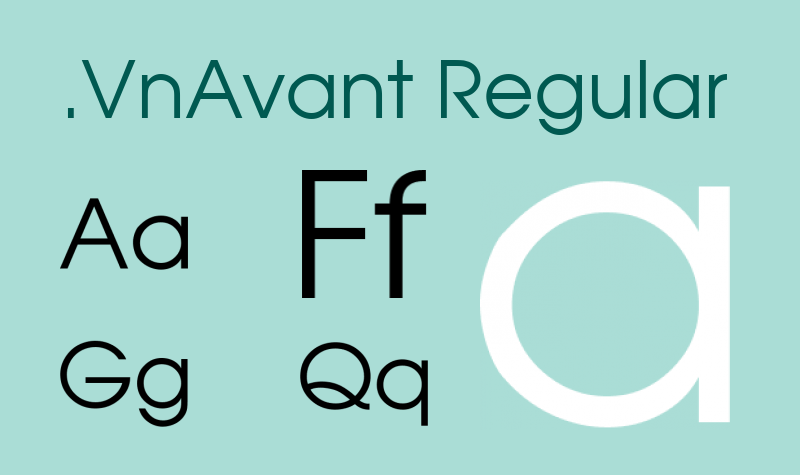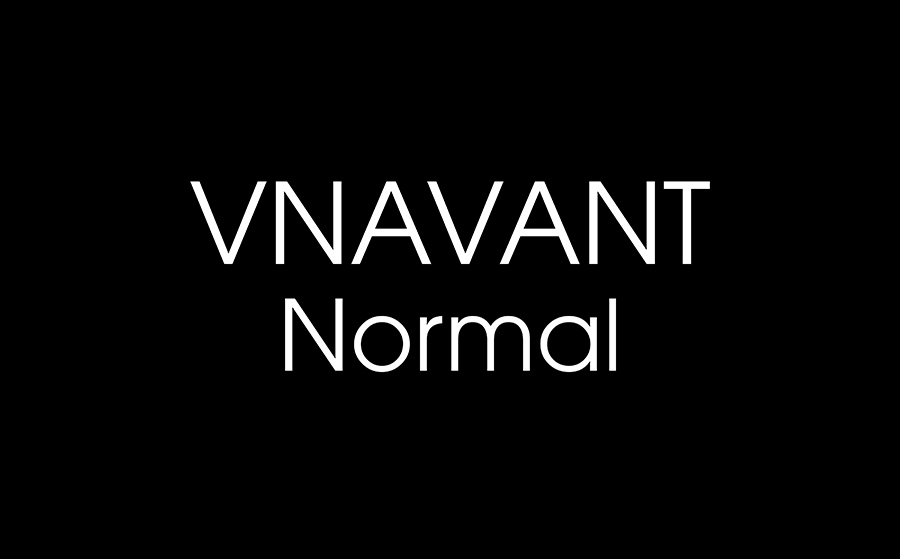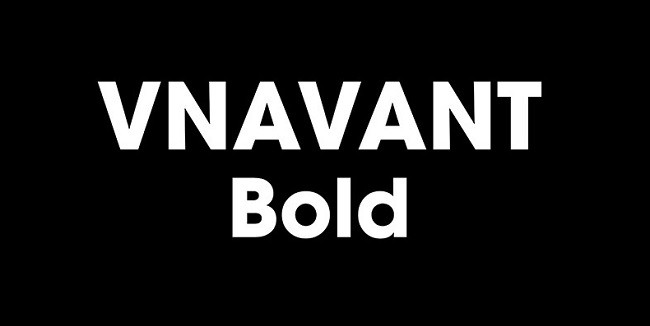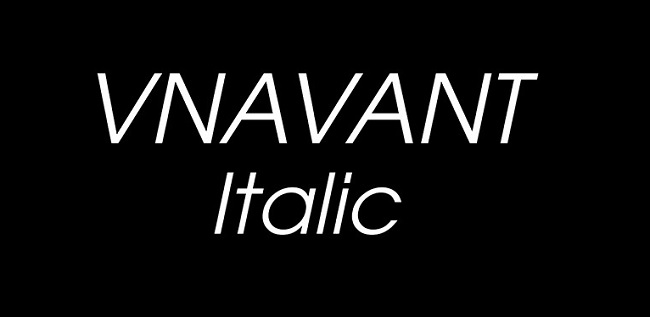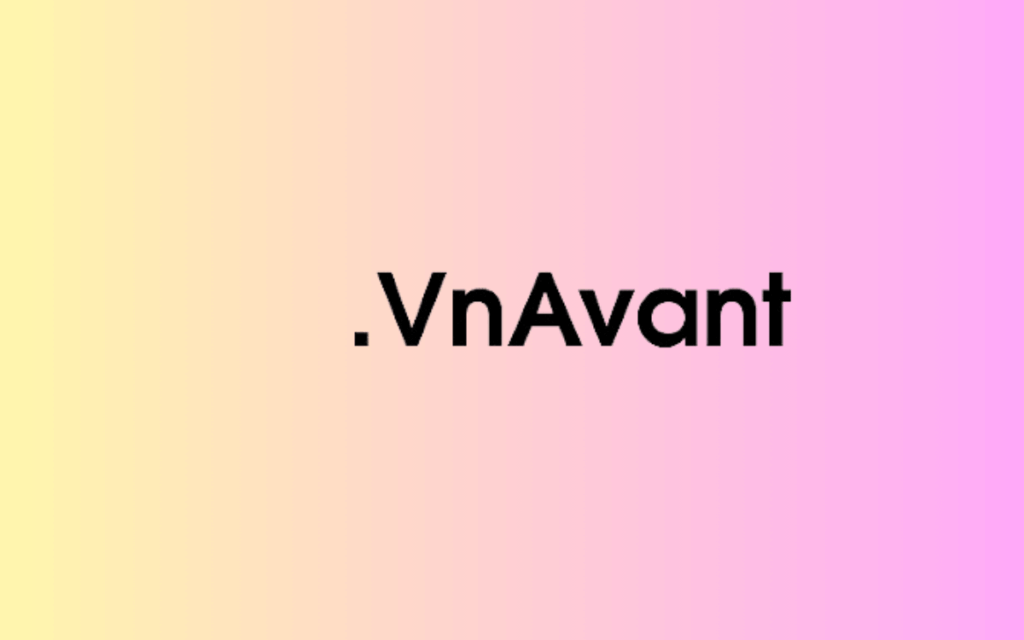
VNAvant là một trong những kiểu chữ không chân thuộc bảng mã TCVN3 (ABC) phổ biến tại Việt Nam, đặc biệt được ưa chuộng nhờ cấu trúc thanh thoát và hiện đại. Việc tải font chữ VNAvant vẫn là nhu cầu thiết yếu đối với các kiến trúc sư, kỹ sư và cán bộ hành chính khi làm việc với các văn bản, hồ sơ dự án hoặc bản vẽ kỹ thuật cũ sử dụng bảng mã tiêu chuẩn Việt Nam.
Font VNAvant
Đặc điểm cấu trúc của font chữ VNAvant trong trình bày văn bản
Điểm đặc trưng của dòng font này chính là thiết kế dựa trên phong cách Avant Garde với các đường nét hình học sạch sẽ, các góc cạnh dứt khoát và tỉ lệ chữ cân đối. Khi thực hiện tải font VNAvant, người dùng sẽ nhận thấy sự mạch lạc trong từng ký tự, giúp văn bản toát lên vẻ chuyên nghiệp và dễ nhận diện. Cấu trúc chữ đứng, ít chi tiết rườm rà giúp cho việc hiển thị các thông số kỹ thuật hay các ghi chú trên sơ đồ mặt bằng trở nên rõ ràng, hạn chế tình trạng rối mắt cho người xem.
Sự ổn định của VNAvant còn thể hiện ở khả năng tương thích tốt với các hệ thống in ấn và phần mềm đồ họa đời cũ. Khác với các dòng phông chữ Unicode hiện đại, phông chữ này sử dụng tiền tố “.vn” để định danh, phù hợp cho việc đồng bộ các biểu mẫu hành chính truyền thống. Đây là lựa chọn hữu ích để xử lý các dữ liệu lịch sử của công trình, đảm bảo tính toàn vẹn của nội dung khi chuyển đổi hoặc nâng cấp các phương án thiết kế nhà lắp ghép và văn phòng container.
| Phân loại phong cách | Geometric Sans-serif / TCVN3 Style |
| Các biến thể tiêu biểu | VNAvant (thường), VNAvantH (đậm) |
| Mục đích phù hợp | Hồ sơ bản vẽ cũ, Tài liệu mầm non, Biểu mẫu hành chính |
03 Ứng dụng thực tế của phông chữ VNAvant trong công việc
Nhờ vẻ ngoài khoa học và tính ứng dụng đặc thù, bộ phông chữ này mang lại giá trị thực tế trong nhiều hạng mục công việc xây dựng và giáo dục:
- Xử lý chú thích bản vẽ CAD cũ: Nhiều bản vẽ kỹ thuật nhà lắp ghép từ các năm trước thường dùng font .VnAvant để ghi chú lớp vật liệu và kích thước. Việc cài đặt font này giúp kỹ sư đọc đúng các thông tin quan trọng, tránh sai sót trong quá trình thi công thực tế.
- Trình bày giáo án và tài liệu học tập: Nhờ nét chữ tròn trịa và rõ ràng, việc tải font VNAvant mầm non rất phổ biến trong ngành giáo dục để thiết kế các bảng chữ cái, giúp trẻ nhỏ dễ dàng làm quen với mặt chữ.
- Hoàn thiện các biểu mẫu báo cáo tiến độ: Trong một số hệ thống quản lý dữ liệu chuyên ngành cũ, VNAvant giúp các bảng biểu hiển thị thông tin mạch lạc, hỗ trợ việc tra cứu dữ liệu dự án thuận tiện.
- Phân biệt kiểu chữ đứng và đậm: Nếu cần làm nổi bật các hạng mục chính trong hồ sơ năng lực, hãy dùng tải font chữ VNAvant kiểu đứng đậm (.VnAvantH). Tránh việc lạm dụng quá nhiều kiểu đậm trong một đoạn văn để duy trì sự thanh thoát cho trang giấy.